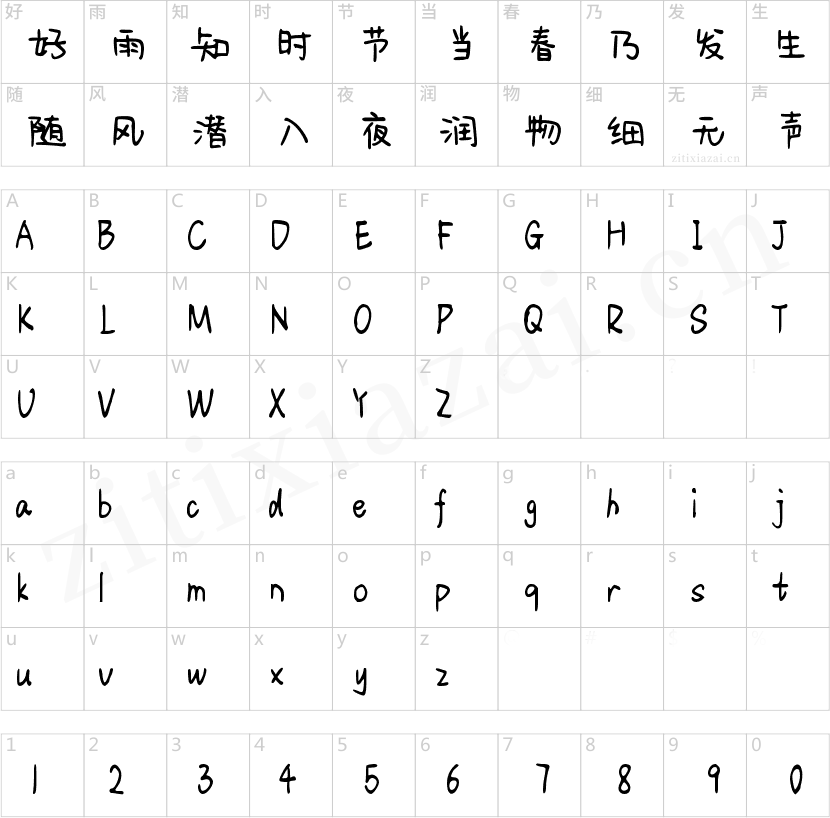
Aa白桃清酒
Aa白桃清酒字体
Aa白桃清酒是一款非常具有艺术性的字体,它的设计灵感来源于对古典艺术的研究,同时又融入了现代字体设计的元素。字形优美,笔画粗细变化自然,给人以大气、典雅的感觉。Aa白桃清酒是一款既传统又现代的字体,它的设计充满艺术感,美观大方,实用性也非常强。无论是对于设计师还是对于普通读者来说,都是一种非常不错的字体选择。Aa白桃清酒适合用于具有艺术感的场合,比如海报、宣传单张、书籍封面等。由于其字形流畅且具有动态感,也适合用于大量的文本排版,如报纸、杂志等。